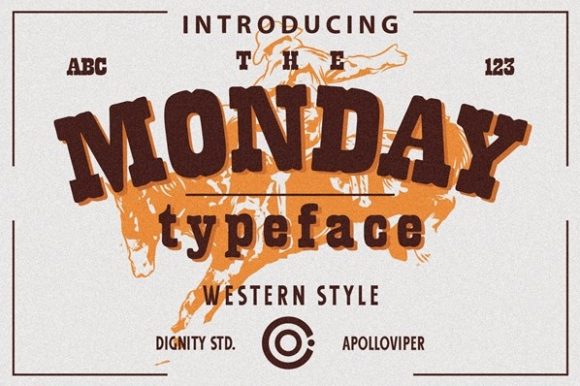
Creativefabrica Monday Font
[Creativefabrica] Monday Font
Понедельник - это жирный, западный шрифт.
Используете ли вы его для дизайна мультфильмов, детских игр, цитат, названий, фирменных наименований, обложек книг, плакатов, или просто для любого творения, требующего прикосновения красоты, этот шрифт - отличный выбор.